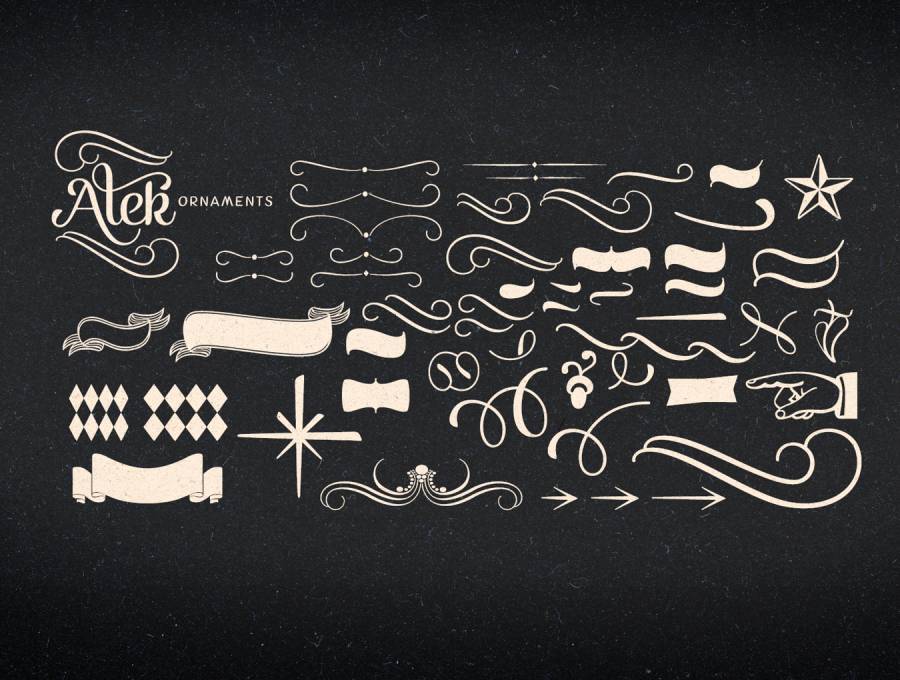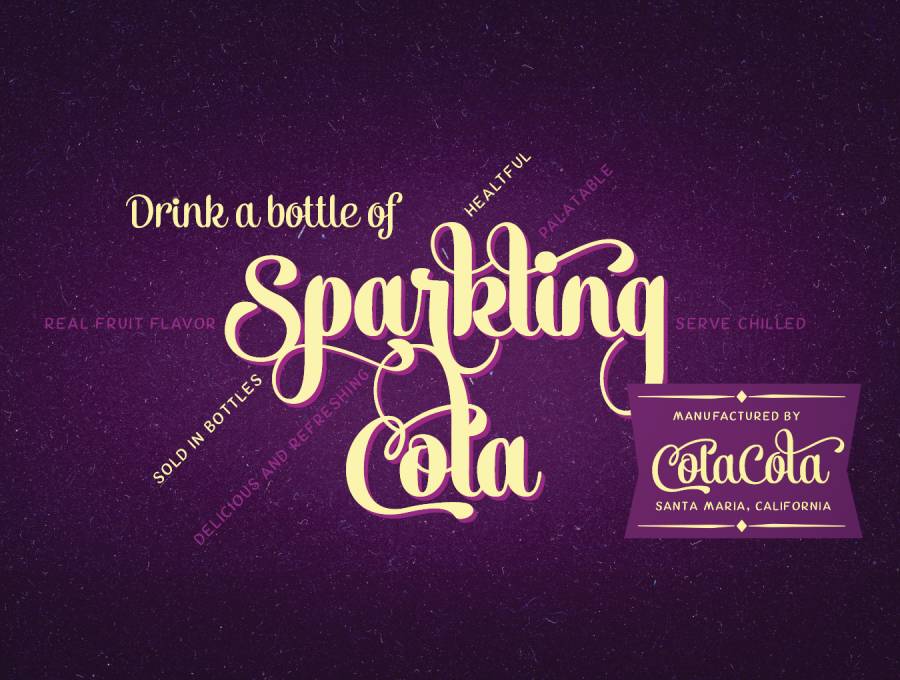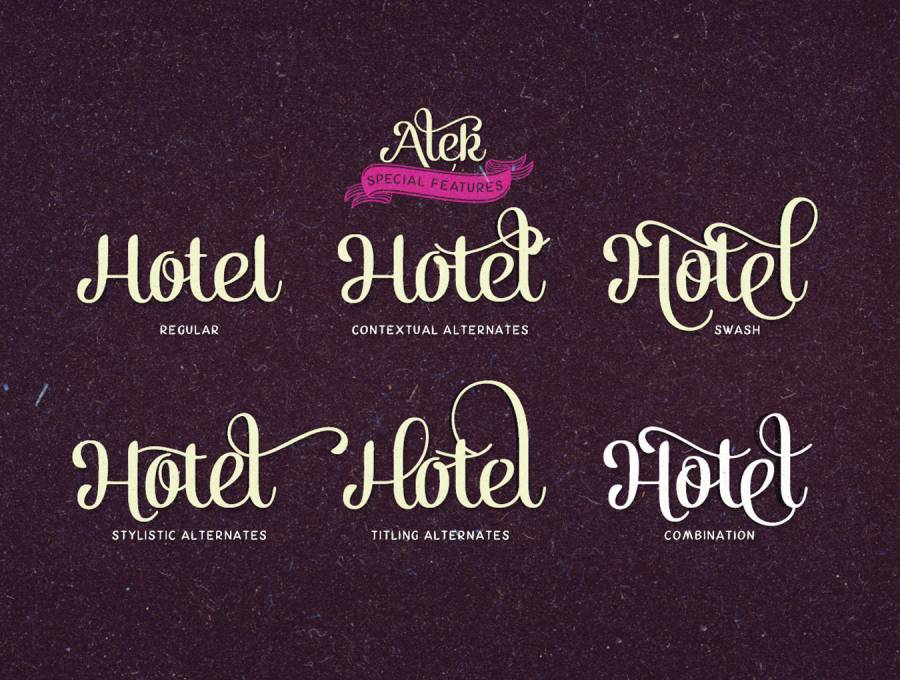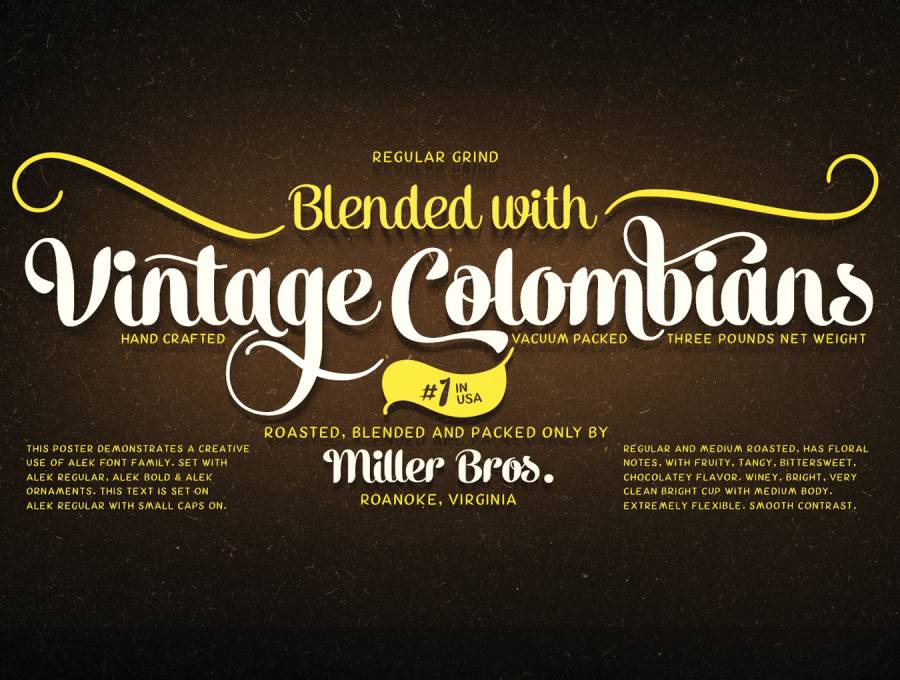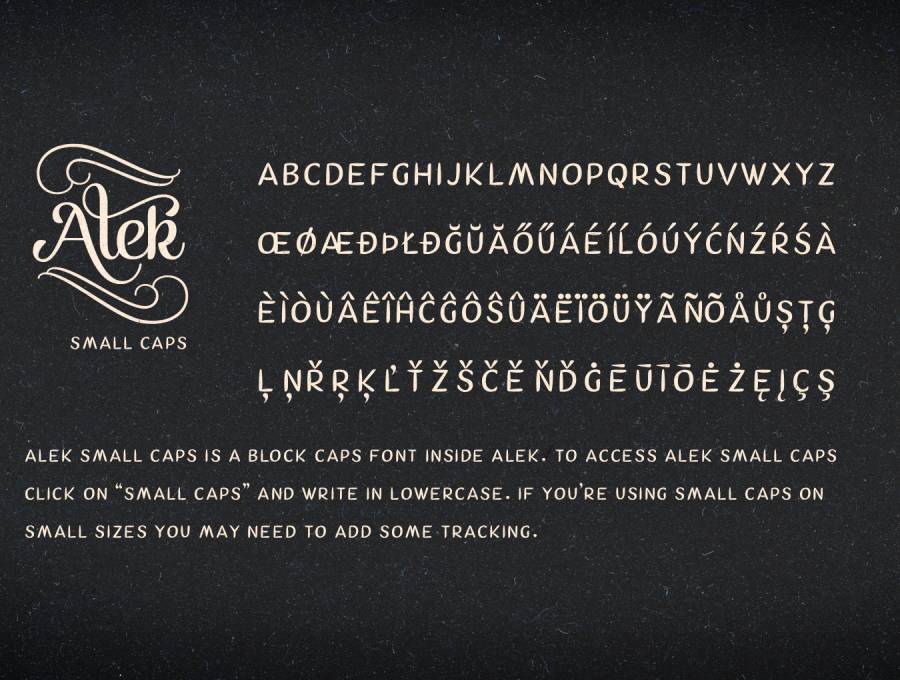
优雅而优雅的正直剧本,阿列克
一个优雅而优雅而又俏皮的直立式脚本系列,由两个重量和装饰组成。 Alek配备了大量OpenType功能:要激活替换项,请在任何OpenType精明程序中单击Swash,Contextual,Stylistic或Titling Alternates或Discretionary Ligatures,Tabular或OldStyle Lining,或手动选择Glyph Palette中的字符。始终保持标准连字以获得最佳结果。搜索结果
将Alek与Alek Ornaments相结合,完成您的设计。打开SmallCaps并以小写形式写入以激活一组旨在支持Alek的块字母。